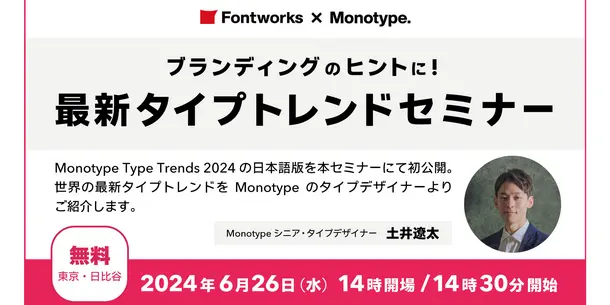
ブランディングのヒントに!最新タイプトレンドセミナー開催のお知らせ
書体と書体テクノロジーのスペシャリストであるMonotypeが毎年発表している、タイプトレンドレポートの日本語版が完成いたしました。
企業のブランディングおよびクリエイティブ担当者向けに、最新のタイプトレンドに関するセミナーを、昨年Monotype へ傘下入りしたフォントワークス株式会社で共同開催いたします。
・書体の最新トレンドが知りたい
・企業・サービスなどのブランディングを考えている
方にぜひご参考いただきたい内容になります。
ブランディングのヒントに!最新タイプトレンドセミナー
Monotype Type Trends 2024 の日本語版を初公開。世界の最新タイプトレンドについて、Monotype シニア・タイプデザイナーの土井遼太よりご紹介します。
2024年版タイプトレンドレポート:
4回目の発表となる今回のレポートでは、書体がどのように社会と結びついているのかを探るため、世界中のクリエイティブな作品を参照し10のトレンドを事例とともに紹介しています。Monotypeの目標の一つであるクリエイターとそうでない人たちとの隔たりを埋めるために、それぞれのトレンドを馴染み深い音楽ジャンルと組み合わせ、デザインしています。書体は、様々な分野に浸透しており、世界が変化するにつれて柔軟に適応し形を変えていきます。このレポートを通して、改めて今の時代にあったブランディングを見直すきっかけになれば幸いです。